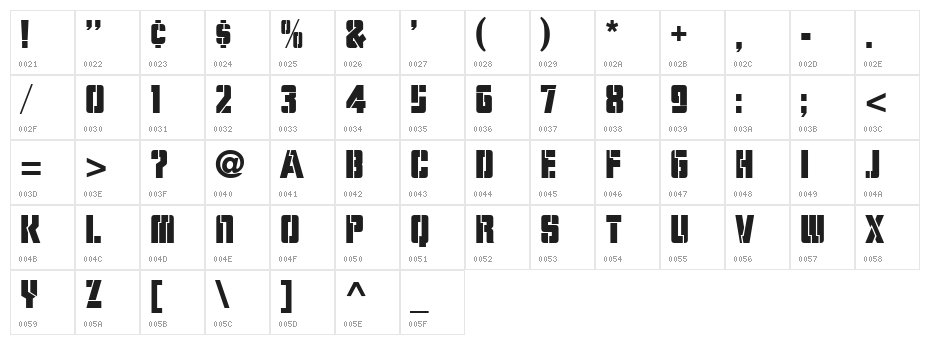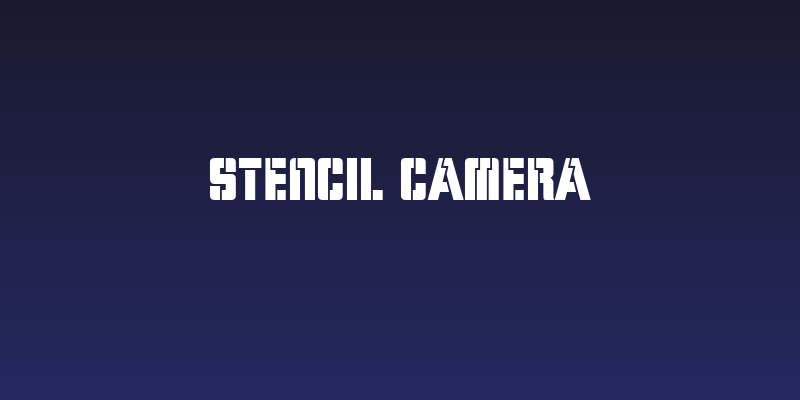
Stencil Camera Font
| Название | Stencil Camera |
| Категория | Futuristic |
| Общий стиль | Industrial, Rugged |
| Рекомендуемые проекты | Ideal for military-themed designs, posters, signage, and branding that requires a strong, industrial aesthetic. |